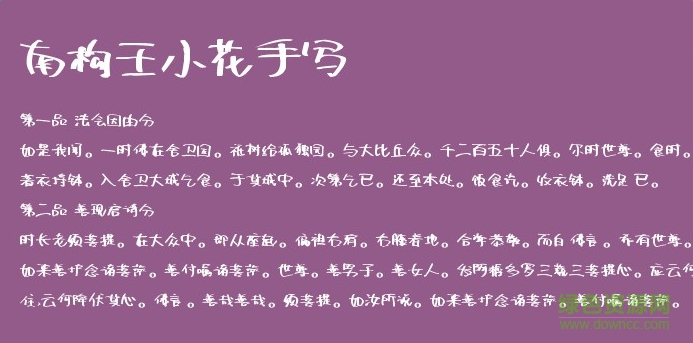
南構(gòu)王小花手寫字體是一款手寫版的葉友根字體,該字體線條細(xì)膩圓潤(rùn),看上去柔美又不失大氣,可用于各種ppt展示中,喜歡的朋友歡迎在綠色資源網(wǎng)下載!
南構(gòu)王小花手寫體介紹
這是一款由王小花手寫的字體,字體風(fēng)格優(yōu)雅中帶著一定的剛毅之美,滿滿的纖柔玉帛風(fēng)融入整個(gè)漢字風(fēng)格!